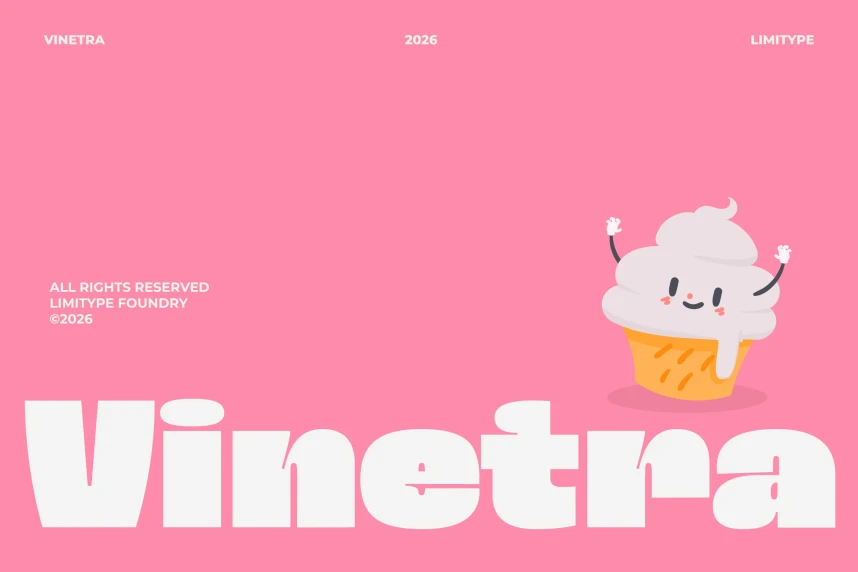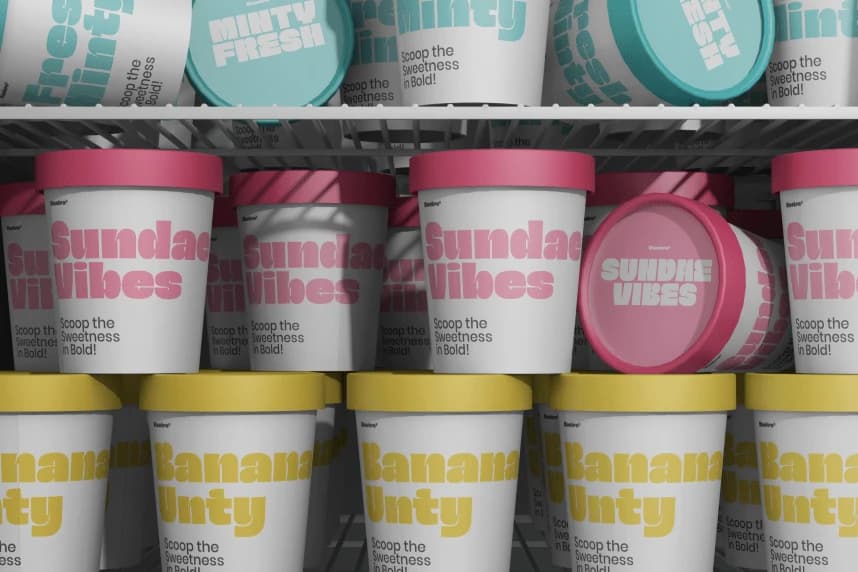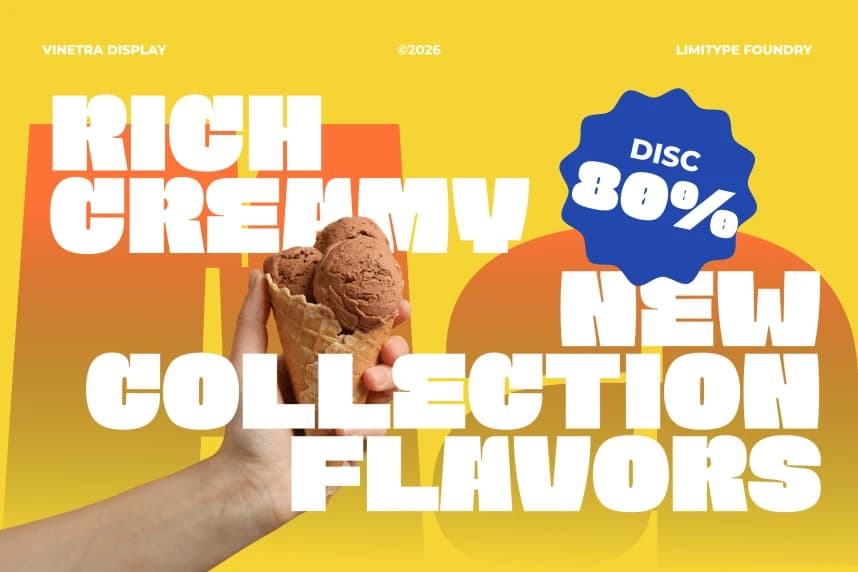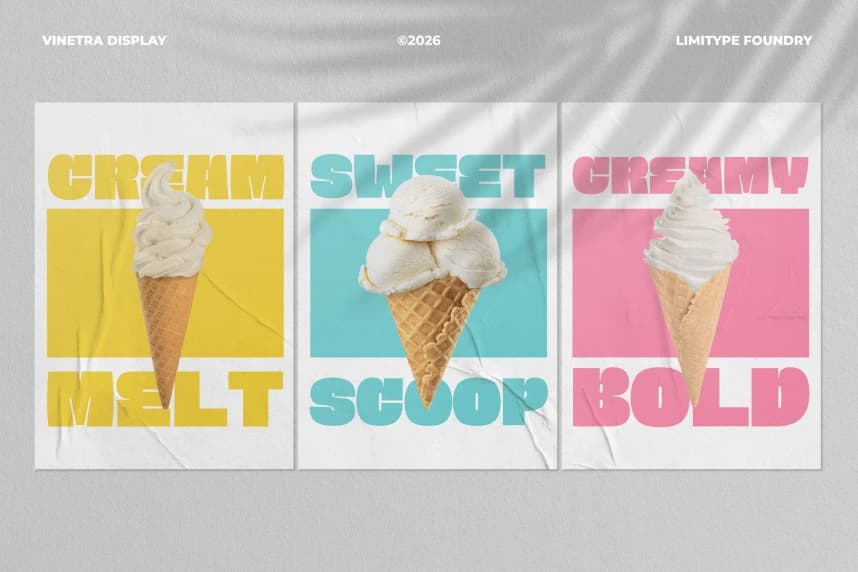
Vinetra – Bold Font
Vinetra - Bold Font, benzersiz şekiller ve çarpıcı bir retro-modern estetiğe sahip cesur bir gösterim yazı tipidir; güçlü bir görsel etki yaratmak için tasarlanmıştır. Kendine özgü karakteri, markalaşma, logolar, posterler, başlıklar ve dikkat çekmesi gereken yaratıcı görsel kimlikler için son derec
Vinetra - Bold Font, benzersiz şekillerle dikkat çekici bir retro-modern estetiğe sahip olan, güçlü bir görsel etki yaratmak için tasarlanmış kalın bir gösterim yazı tipidir. Belirgin karakteri, markalaşma, logolar, posterler, başlıklar ve dijital ile basılı tasarımlarda dikkat çekip öne çıkması gereken yaratıcı görsel kimlikler için son derece uygundur.
Vinetra – Bold